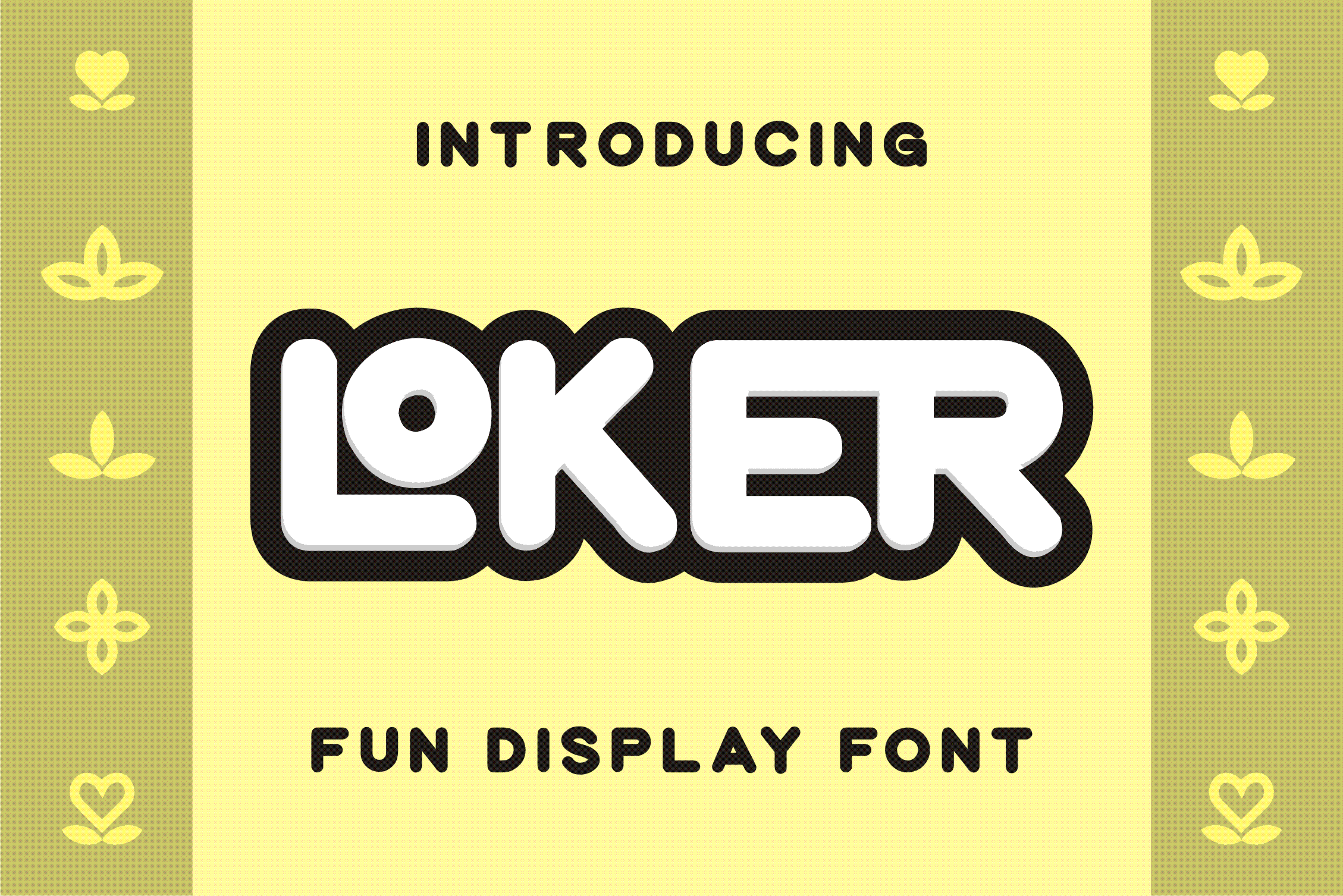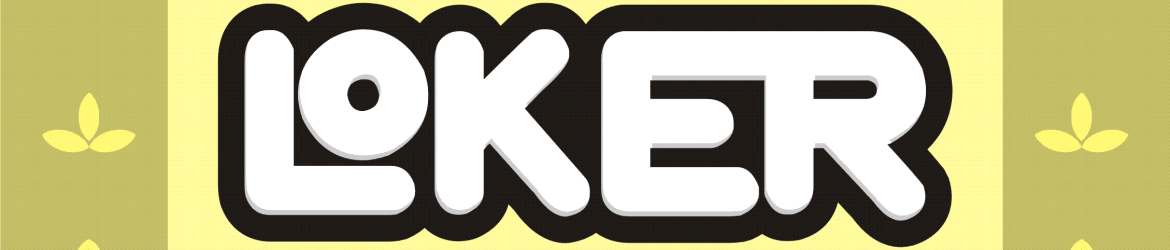
Loker Font – Download Grátis
A ‘Loker Font’ é uma escolha ótima para quem busca estilo e criatividade sem comprometer a facilidade de uso. Composta por linhas espessas e formas arredondadas, esta fonte display traz uma textura vibrante que se adapta perfeitamente a diversas aplicações de design gráfico. Seja você um profissional ou um amante da arte digital, essa fonte oferece liberdade para expressar sua identidade visual em projetos variados. Adicione-a ao seu portfólio e observe como ela destaca os seus trabalhos. Composta por letterfiastudio, a ‘Loker Font’ é uma adição incrível à sua coleção de recursos gráficos disponíveis para download.